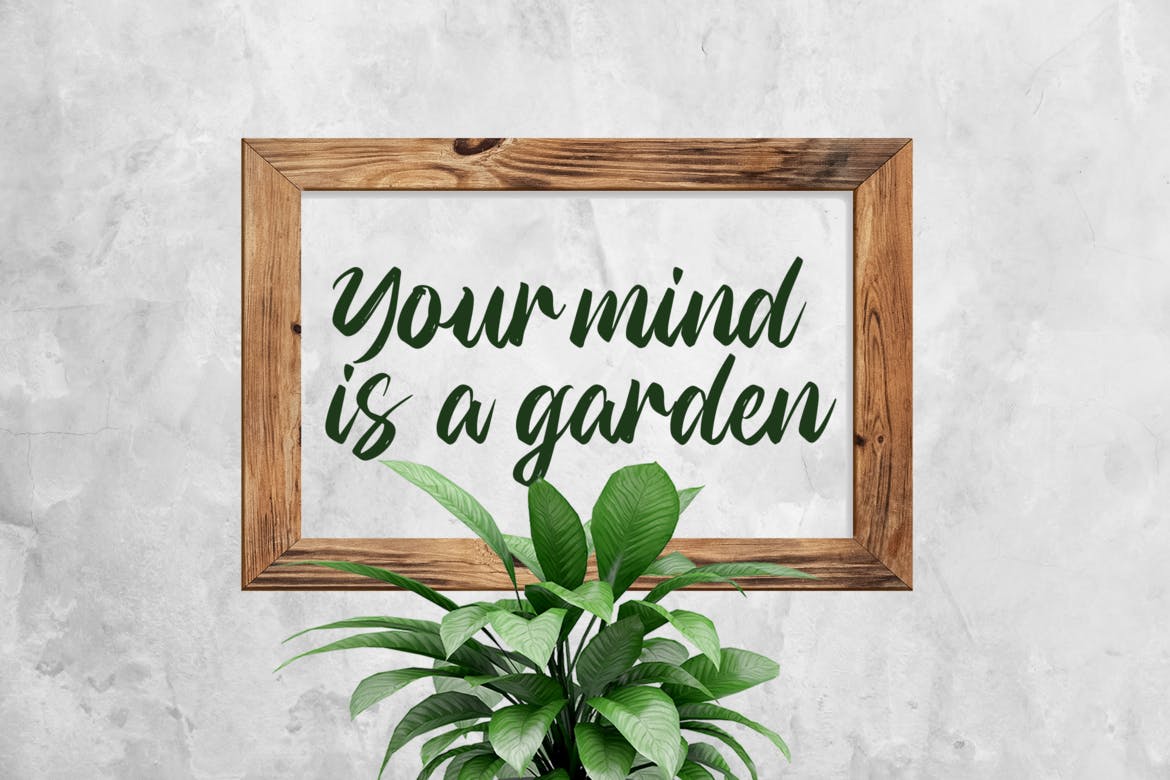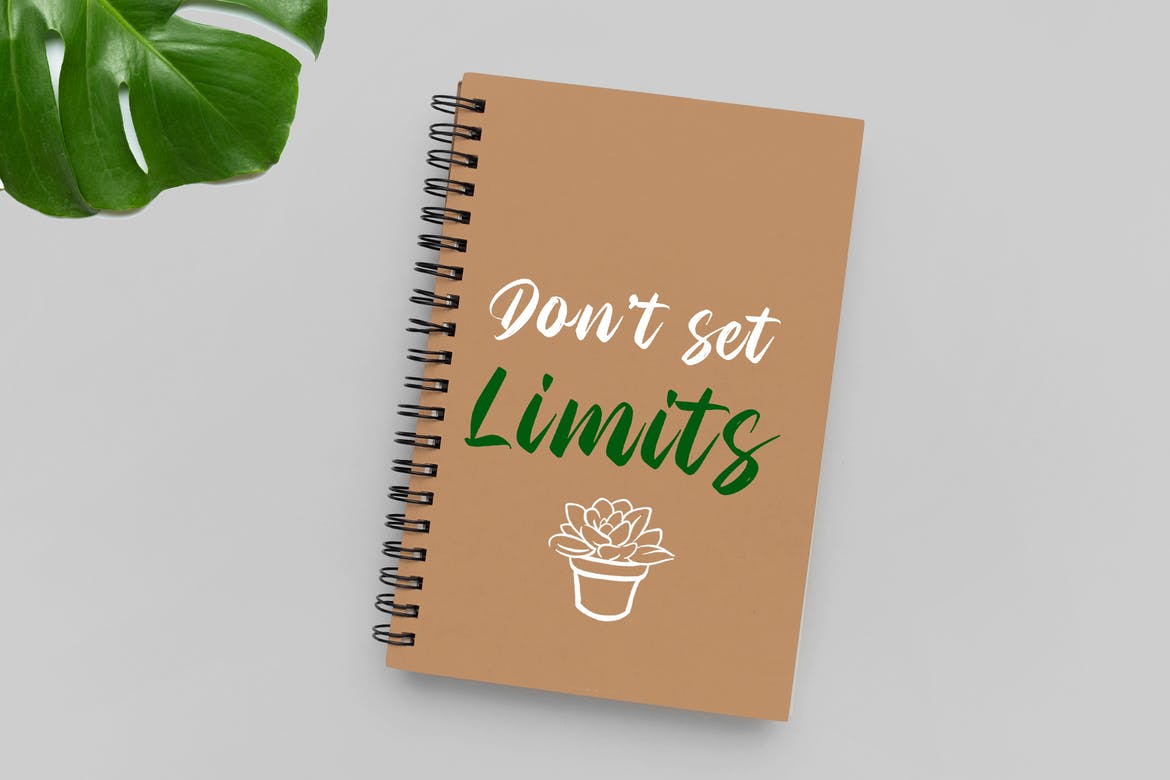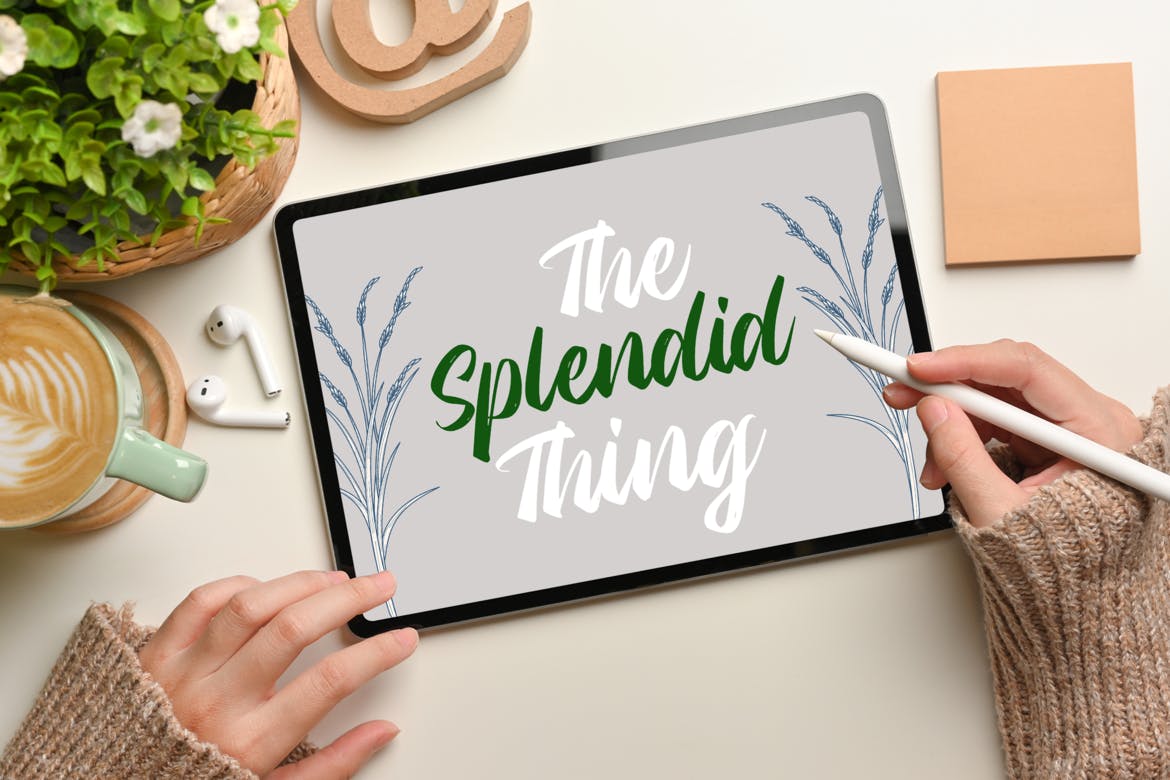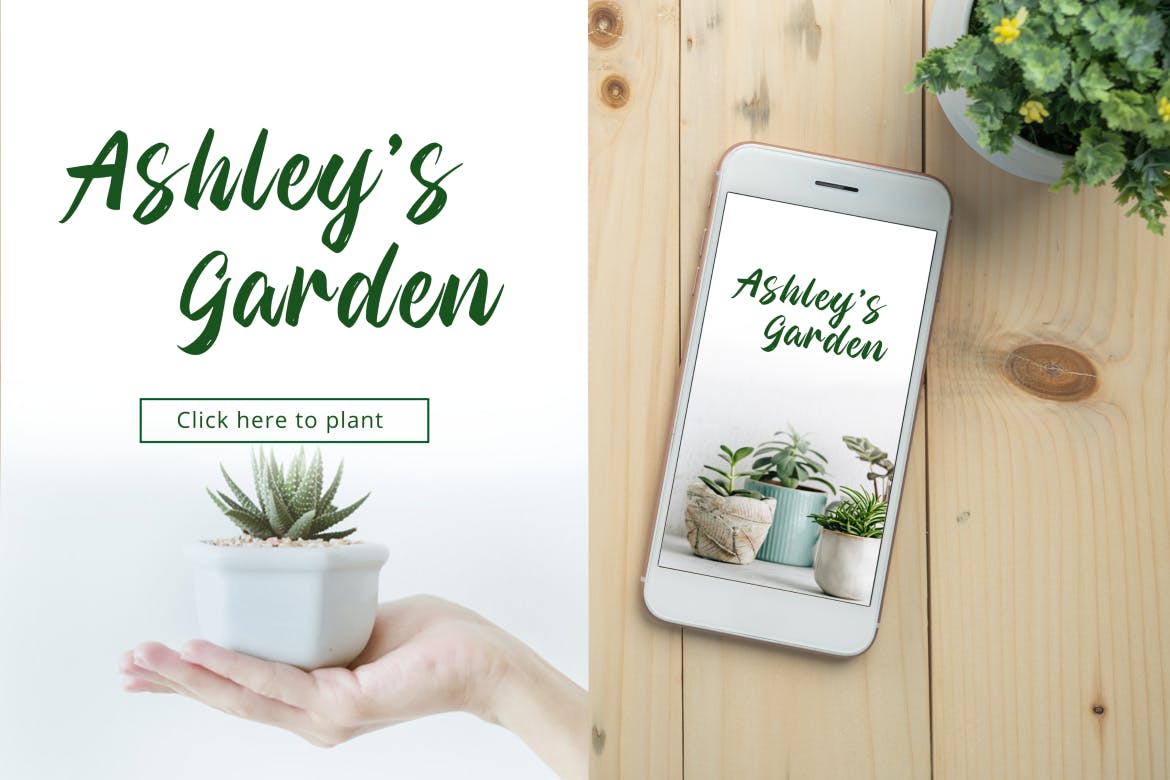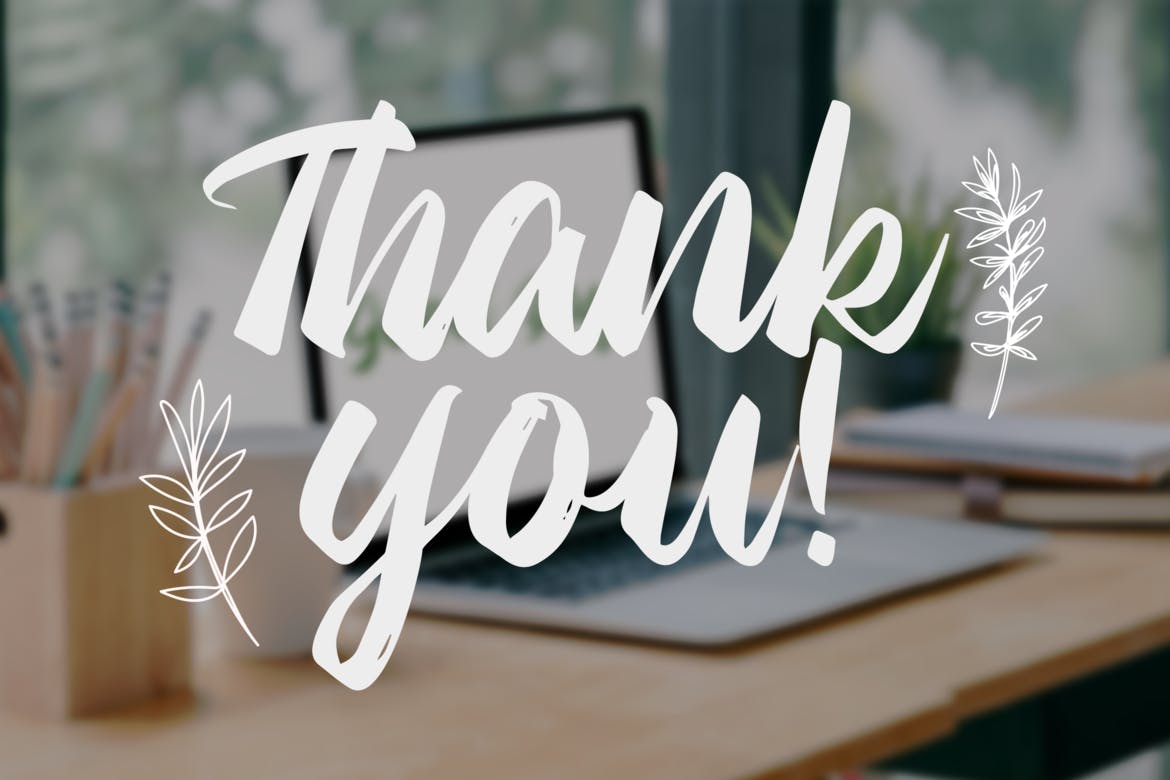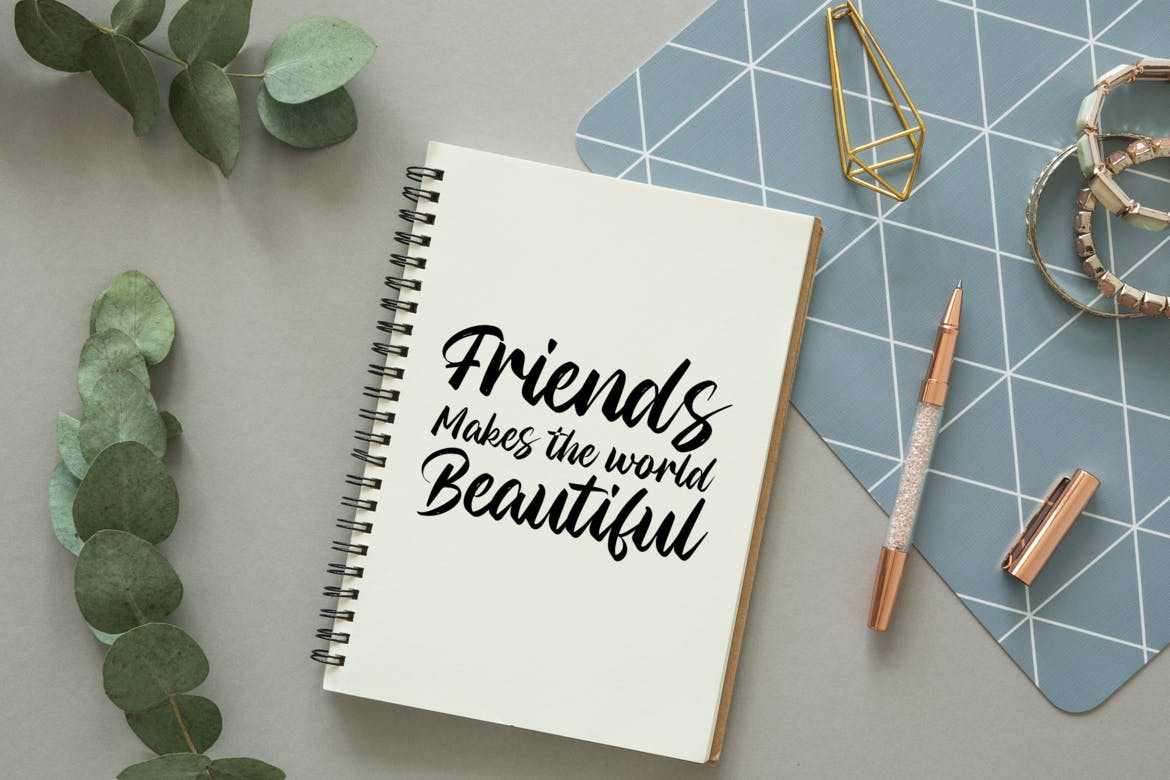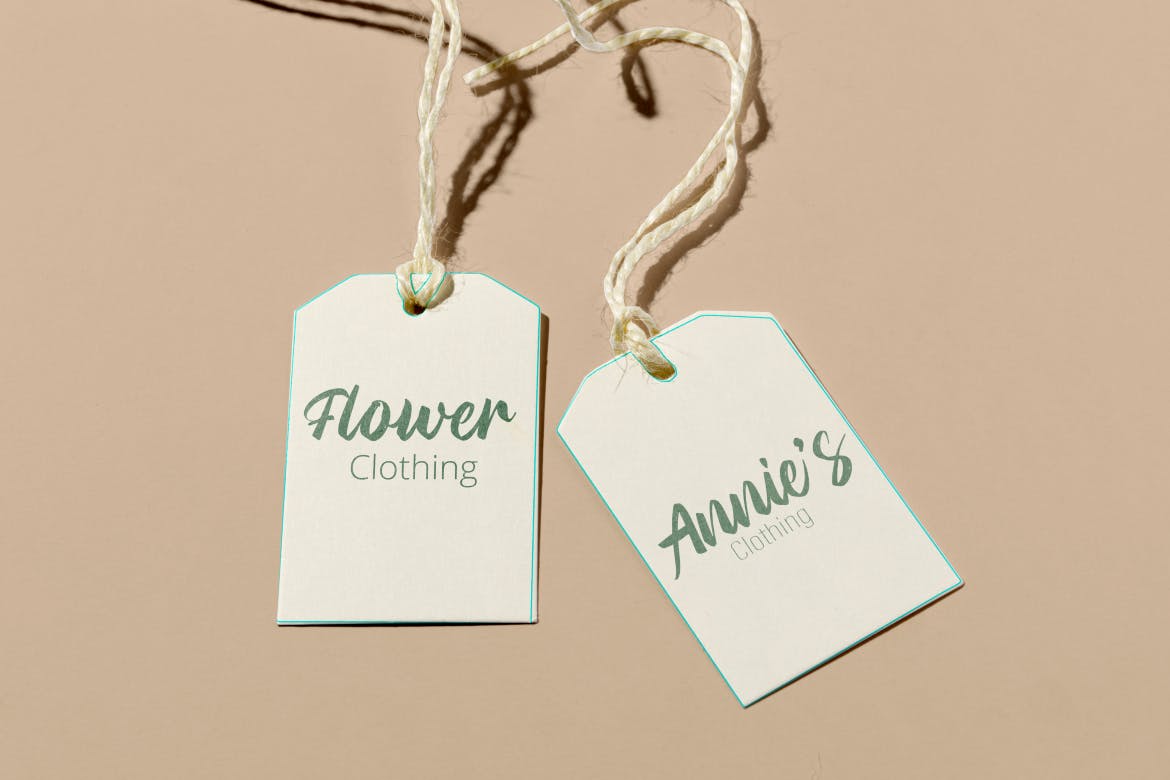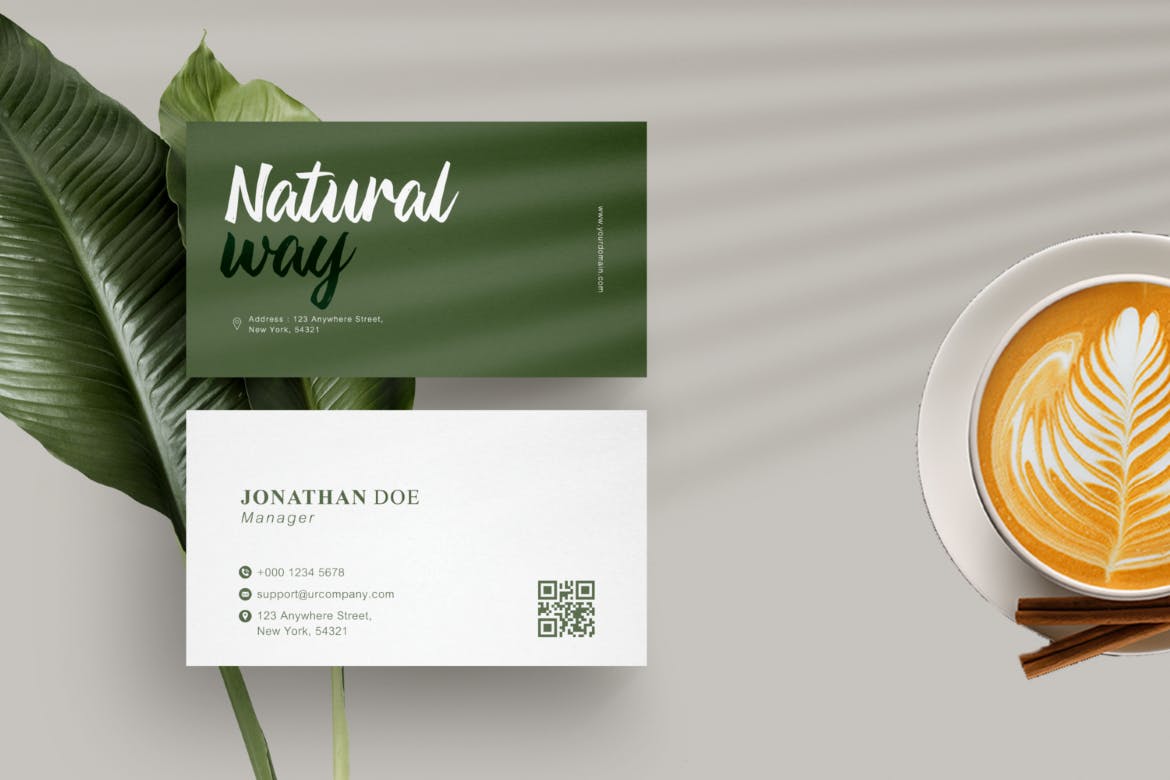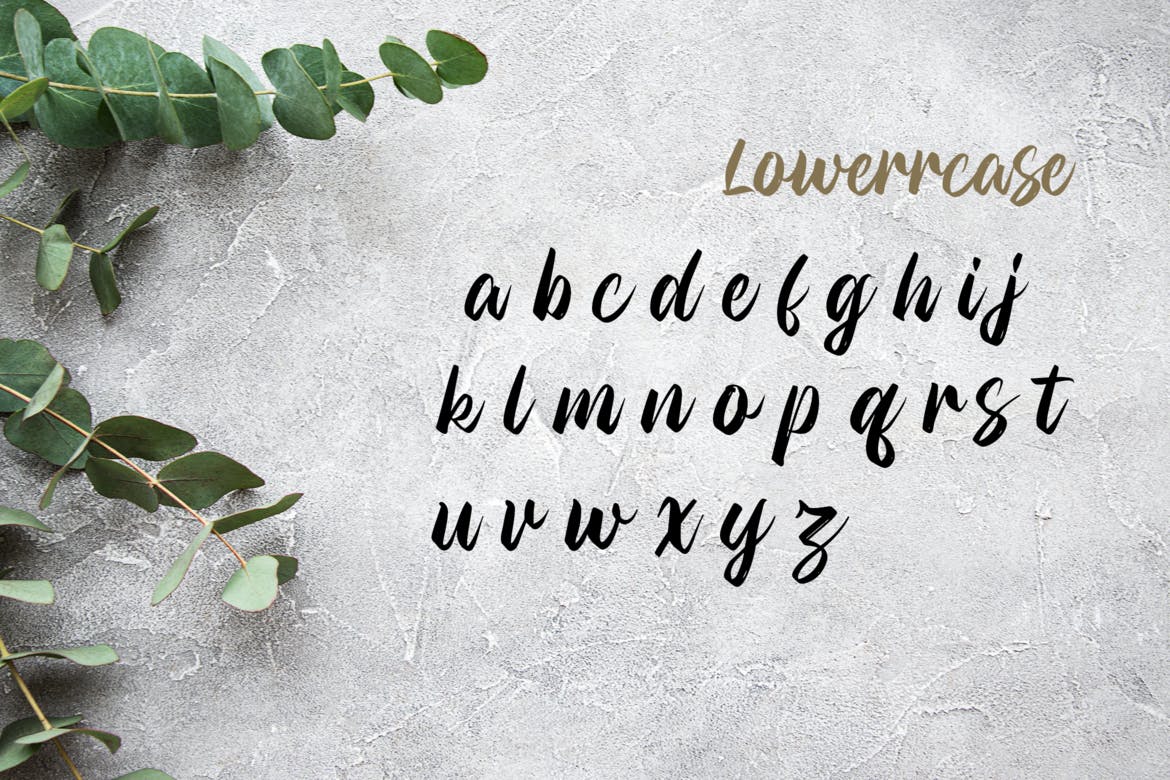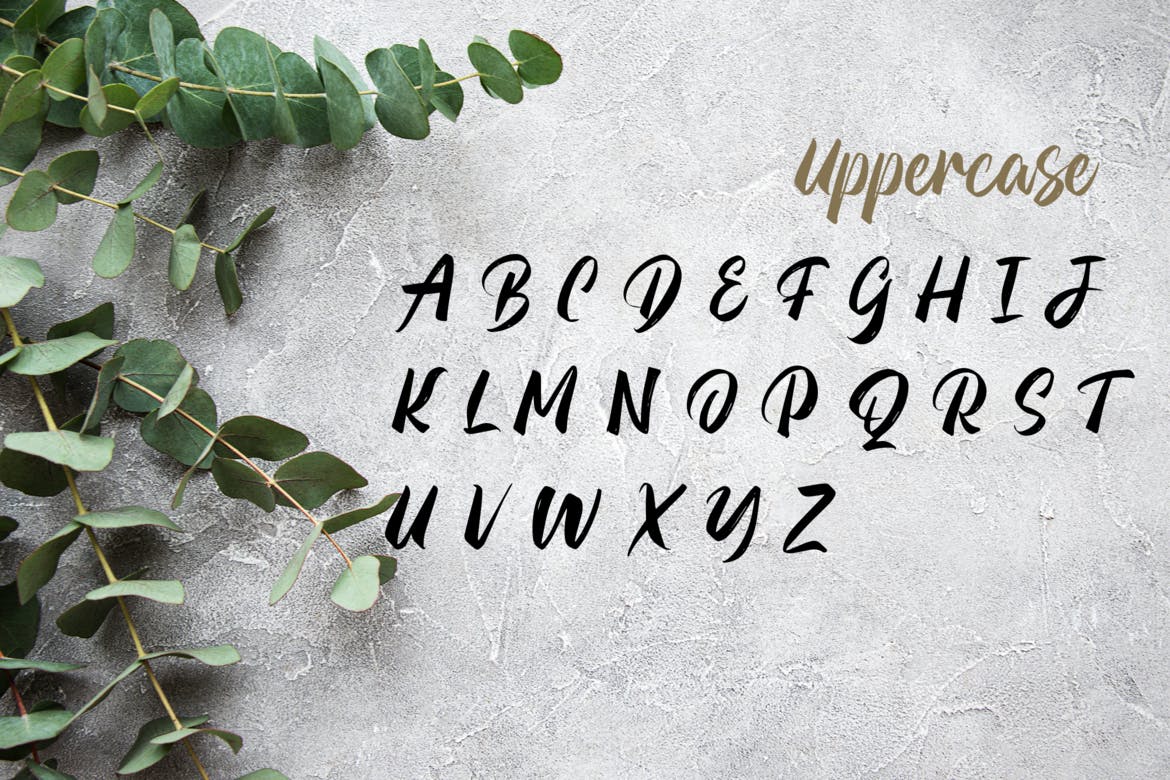
آیا به دنبال یک فونت خوشنویسی خلاقانه هستید که به سرعت جلب توجه کند؟ چه در حال طراحی دعوتنامهای برای یک رویداد باشید و چه بخواهید کارت ویزیت خود را زیبا کنید، انتخاب فونت مناسب بیشتر از صرفاً انتقال کلمات اهمیت دارد.
معرفی میکنیم Theodore - یک فونت خوشنویسی مدرن.
این فونت هنری و شیک، انتخابی فوقالعاده برای تمام افرادی است که به خلاقیت علاقهمندند. Theodore به خوبی برای هر دو حالت چاپ و وب کارایی دارد و شما میتوانید از آن برای دعوتنامهها، تبلیغات، کارتهای چاپی، لباسها، صفحات وب، اپلیکیشنها، تبلیغات و هر آنچه پروژه شما نیاز دارد، استفاده کنید.